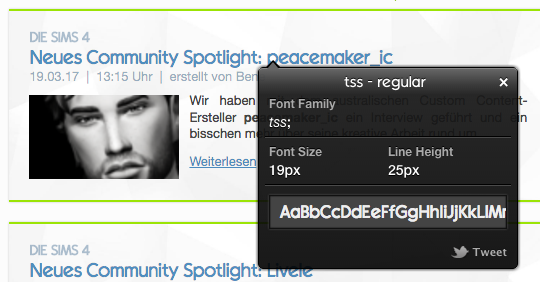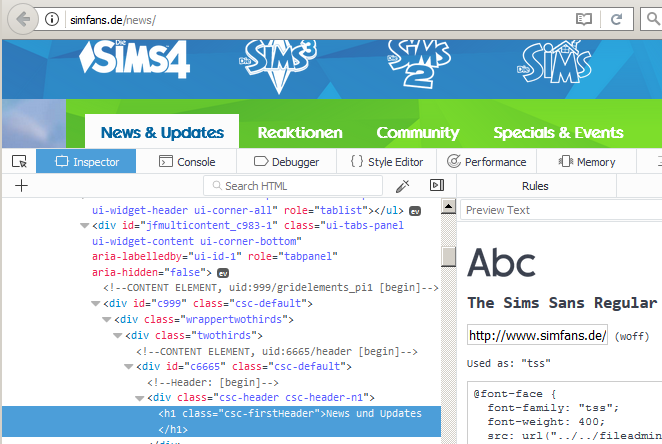
Dünne, bekannte Schriftart gesucht (The Sims Font)
Hallo, ich suche aktuell eine relativ dünne Schriftart, die ihr im Anhang sehen könnt :D
Die Schriftart benutzt SimFans.de, aber das ist eine Schriftart, die man irgendwo herunterladen muss, weil sie in diesem Video von Karoline Kebekus ebenfalls sehen kann:
Wisst ihr, welche das sein könnte? :D
TheMix von Lucas de Groot.
Edit: Semibold, schätze ich.
Ralf, danke für den Tipp, diese ist es aber leider nicht. Die Schriftart habe ich selber, sie enthält aber keine Kleinbuchstaben. Ich habe jetzt als Ersatz "Century Gothic" genommen, die sieht fast identisch aus. :)
»Comedy & Satire« ist in TheMix gesetzt. Und auf SimFans.de ist The Sims Sans Regular als Webfont eingebettet. Und der Font enthält Kleinbuchstaben.
Das kann man bestätigen, hier heißt sie in der Kurzform "tss"